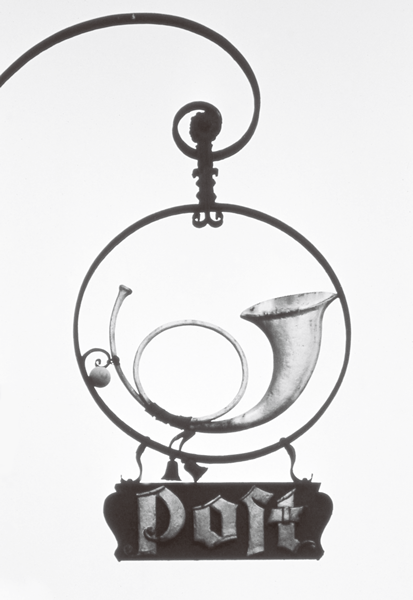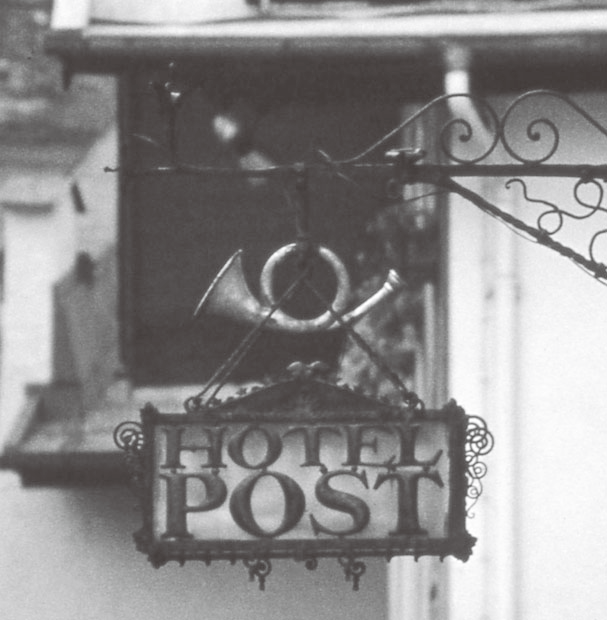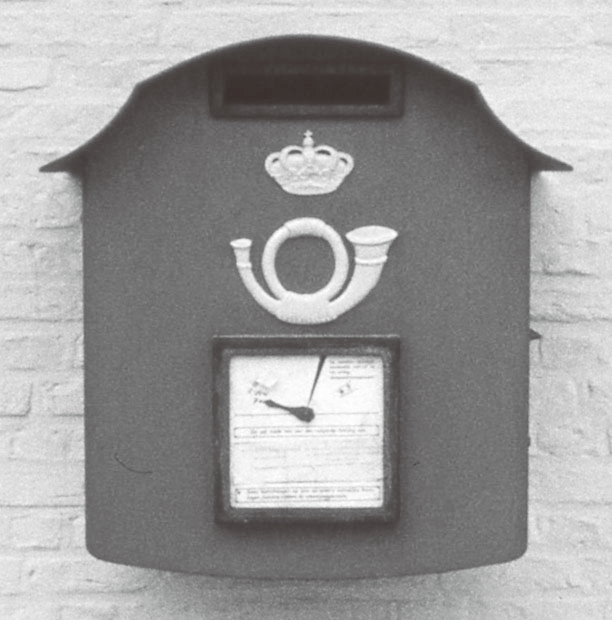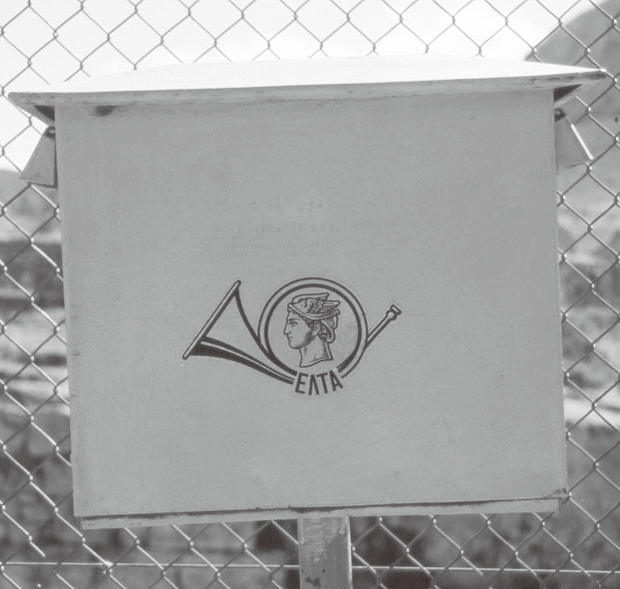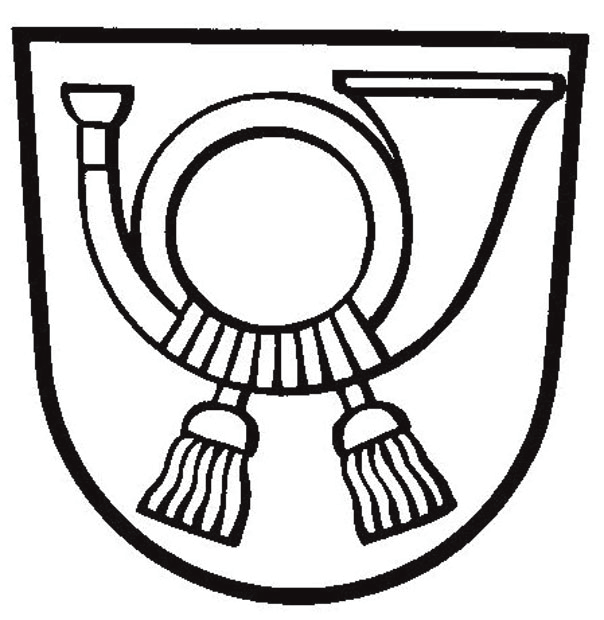
町に到着したときに知らせるために吹いたもの 1965撮影
人は誰でも楽しみにしていた便りや渡されて嬉しかった手紙の想い出があるだろう。現在は手紙よりメールや携帯電話の方が早く便利なので手紙を書かなくなっている人も多くなっている。手紙は時を経てから読み直す楽しみがある。手紙の歴史は古くからあった。西暦1世紀にギリシャ語で書かれたパウロの14通の手紙が有名で世界中で広く読まれている。「すべての人に対して平和を求めること、互いに愛し合うことのほかはだれにも何も負わない」などクリスチャン生活に必要な忠告が含まれている。
ヨーロッパを旅行すると郵便局やポストにホルンのマークが使われているのに気づく。どうしてホルンが使われているのだろう。これは中世の郵便業務の歴史からひもとくことになる。ヨーロッパの手紙は羊皮紙が用いられていた。高価であったため手紙を出す人たちは限られていた。12世紀以後になると中国で発明された製紙技術が伝えられ、13世紀後半にはイタリアで紙が製造され、14世紀にはライン地方に製紙工場が広まり、1300年頃にはドイツで貴族が手紙を書くようになり、人と人とのコミュニケーションとして大切な役割を果たすようになった。王の手紙は使者が箱に入れて王の紋章をつけた枝を持って街道を配達人として運んだ。庶民の手紙を町から町へと運んだのは職人や巡礼や大道芸人だった。中世の中ごろから手紙類が増加するにしたがって、農民が交代で配達人として働くようになった。ライン地方では肉屋が肉の仕入れのために農家を回る時に郵便を引き受けた例もあった。配達人は普通男性だったが、市の内外の近距離には女性も用いられた。大都市の商人は初期は個別に配達人を雇っていたが、ギルド制度が成立してから共同の配達制度が出来るようになって、定期便が使えるようになった。フランクフルトでは1476年から市民も手紙を託することが出来るようになり、現在の制度に近づいた。いよいよ郵便業務にホルンが登場する場面について阿部謹也著「中世の窓から」は次のように書いている。「肉屋が肉の買い付けに農村にやってきたとき、小さな角笛を吹いて到着を告げ、売り手に知らせたことからこの習慣がはじまったといわれています。1490年にインスブルックからオランダへ行く途中で旅籠に到着した飛脚が角笛を吹き、待機していた次の飛脚がそれを聞いて起きてくることが『メミンゲン年代記』にでてきますが、これが郵便と角笛を結ぶ最初の史料です。ウィーン・ブリュッセル間に、トゥルン・タクシスの郵便業がはじまり、近代的な郵便制度の先駆が出来るのが1516年ですが、タクシスの郵便業が角笛を使うようになるのは1615年のことで、今でもドイツ連邦郵便はラッパをしるしとしています。シューベルトの『冬の旅』の一曲、『郵便馬車』にも、主人公が角笛の鳴るのを聞くたびに恋人からの便りを待って胸をときめかせているありさまが巧みに歌われています。」
また別の資料、西川潔著「ヨーロッパ伝統の看板」には「馬上でポストホルンを吹く人や郵便馬車とポストホルンが、ホテルの看板にたくさん残っている。これは昔、郵便馬車に旅人も乗っていたからである。……郵便馬車は乗合馬車を兼ねていた。御者やその助手がポストホルンを吹いて到着や出発、座席の数や馬の数を知らせたり、街中では道行く人に注意を呼びかけるクラクションの役目もした。」と郵便業務とホテルとの関係を伝えている。
日本の紋章には角笛、ラッパ、ホルンは無いが、似たものとしてホラ貝がある。これは音によって知らせる楽器の仲間であるが、戦国時代に戦陣の号令を与えたり、山伏の道中や人を集めるために吹くことに使われた。西洋の紋章にはホルンがある。一つのもの、三つのもの、人魚が吹くホルンもある。日本の郵便業務は明治4年(1871)に郵便の父と呼ばれている前島密によって創設された。シンボルマークは「逓信」の頭文字「テ」をデザインしたもので明治20年(1887)に定められた。
郵便業界は大きく変わろうとしている。電子メールや自由化によって英国の地方郵便局が閉鎖されている。ヨーロッパで広く使用されているシンボルのホルンは生き残れるだろうか。